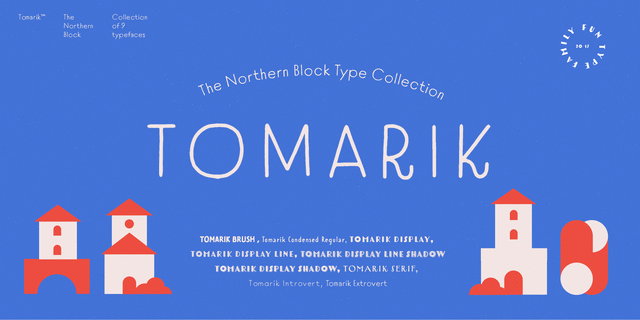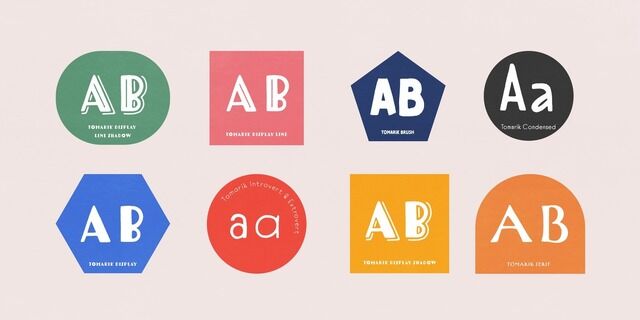
Відкритий гротеск, намальований ручкою – частина яскравої колекції рукописних шрифтів Томарік. Грайливе доповнення будь-якого творчого проекту. Шрифтової набір, зібраний для роботи за принципом «обирай і змішуй», він пропонує велику різноманітність стилів і характерів. Томарік містить дев'ять різних накреслень з латинкою та кирилицею і включає функції OpenType, такі як верхні та нижні індекси і дроби. Шрифт розробила Марія Пігулевська у 2017 році. Tomarik™ є торговою маркою компанії The Northern Block.
Особливості сімейства Tomarik ExtrovertХіт десятиліття:
Асоціації з сімейством Tomarik ExtrovertЯкості та характер:
Діяльність: